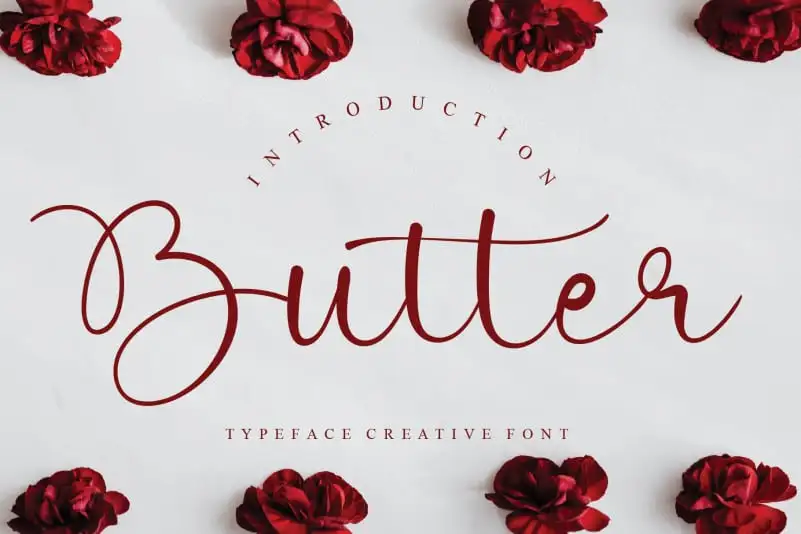
Butter Calligraphy Font – Download Grátis
A Fonte Butter Calligraphy é uma criação única e especial que transforma seu design de texto em uma arte visual envolvente. Com sua linhas fluidas e delicadas, essa fonte criativa adquire um toque distintivo e sofisticado ao decorar qualquer projeto editorial ou publicitário. Ideal para estilos mais elaborados como wedding invitations, logos personalizados, gráficos de moda ou até mesmo letras decorativas em livros de design, a Butter Calligraphy oferece uma experiência única que vai além da funcionalidade simples da tipografia. Desenvolvida pelo Designer CreativeLetter, essa fonte é perfeita para aqueles buscando adicionar um toque único e personalizado aos seus projetos gráficos. Com sua abordagem criativa, a Butter Calligraphy não apenas se destaca no mercado de fonts, mas também oferece uma experiência inovadora e memorável.